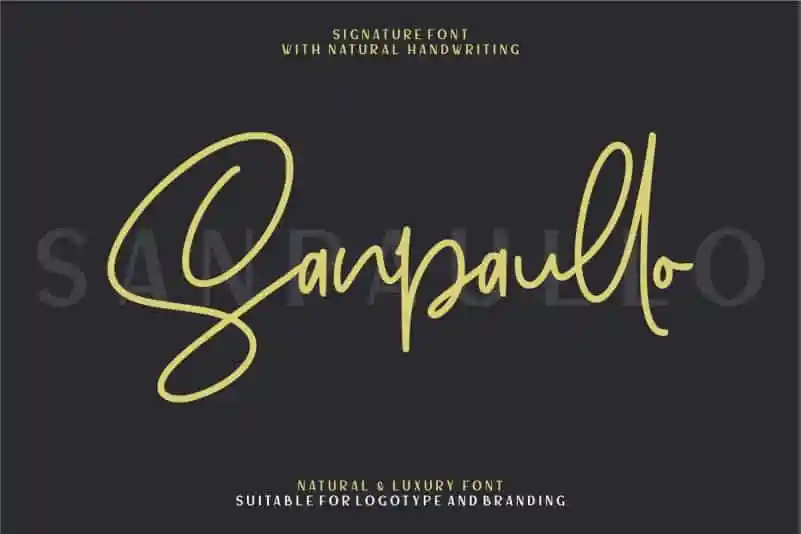
Sanpaullo Signature Font – Download Grátis
A Sanpaullo Signature Font é uma herança elegante do estilo de letra Garisman Std, desenvolvida para criar designs que chamem a atenção. Ela se destaca como um tipo de script natural e feminino perfeito para logos, convites, cartelas, desfiles de casamento, postagens nas redes sociais, anúncios, embalagens de produtos, design de produto, etiquetas, fotografia, marca d’água, eventos especiais ou qualquer aplicação que você possa imaginar. Esta font se destaca por sua facilidade em fazer um design brilhar, tornando-se perfeita para qualquer projeto visual que desejamos dar uma personalidade única. Com o Sanpaullo Signature Font, a elegância do Garisman Std ganha vida em seu próprio estilo natural e autêntico, criando uma paleta de opções incrivelmente versátil para designers gráficos.